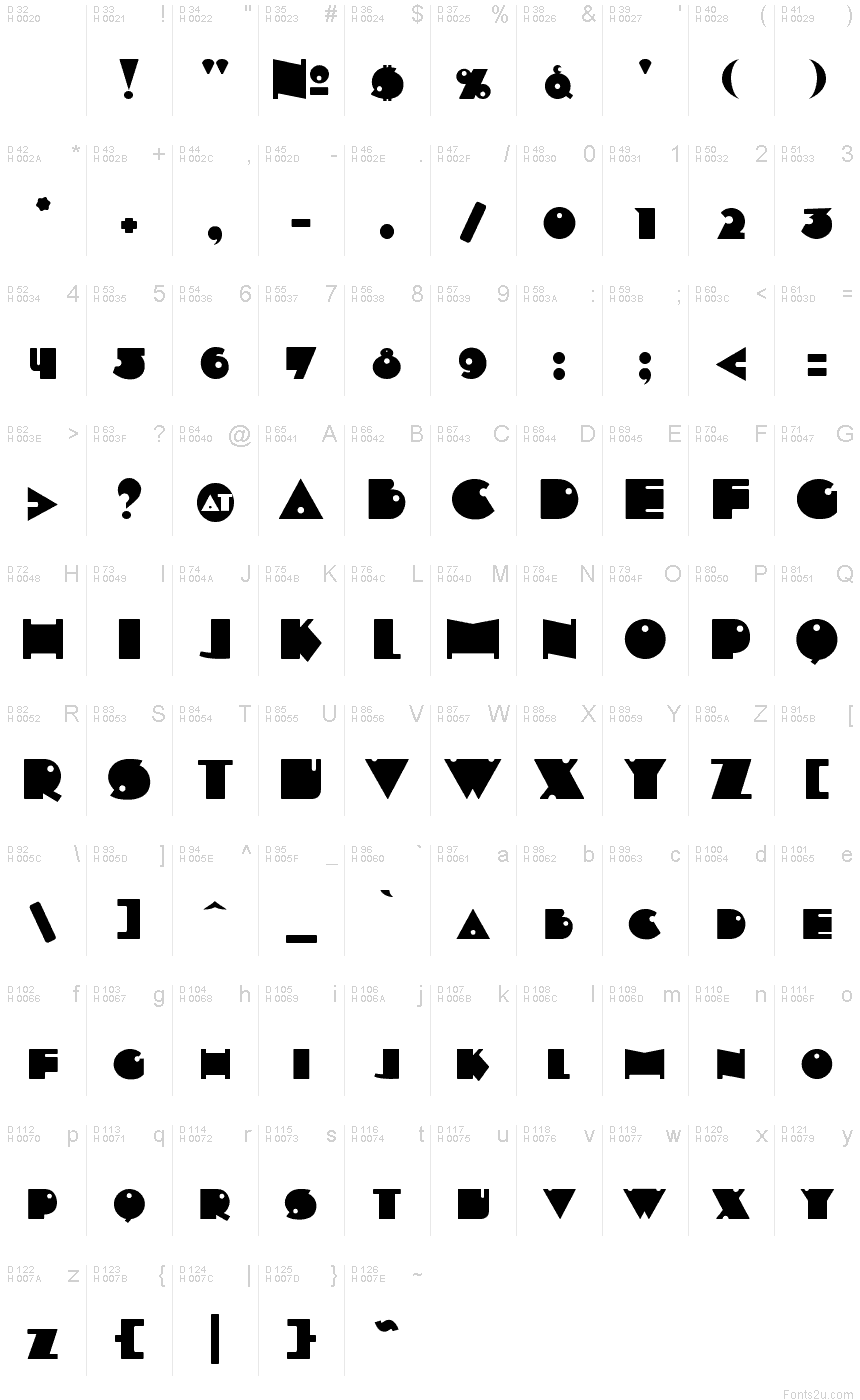
Independant - Small Caps
Independant Small Caps od Phynette & Apostrophic Laboratories to darmowy krój displayowy w stylu retro, inspirowany europejskimi szyldami z lat 30. XX wieku. Masywne kapitaliki, tępe narożniki i wyraziste, koliste wycięcia sprawiają wrażenie liter wybitych w metalu, nadając każdemu słowu industrialny, namacalny charakter. Rytm znaków jest zwarty i blokowy, dzięki czemu nagłówki przypominają solidne banery z tuszu, a nie lekki tekst na stronie.
Wykorzystując Independant Small Caps, możesz przemycić klimat klasycznych witryn sklepowych i kinowych afiszy do swoich logotypów, plakatów, opakowań, nagłówków redakcyjnych, okładek płyt czy systemów oznaczeń. Ten darmowy font świetnie sprawdza się w dużych rozmiarach, gdzie jego nietypowe światła wewnętrzne i wąskie odstępy mogą zdominować cały układ. W przypadku dłuższych tekstów łącz go z nowoczesnym, czystym krojem bezszeryfowym w mniejszym rozmiarze, pozwalając Independant Small Caps przejąć kontrolę w najważniejszych, pełnych wyrazu momentach na stronie lub ekranie.